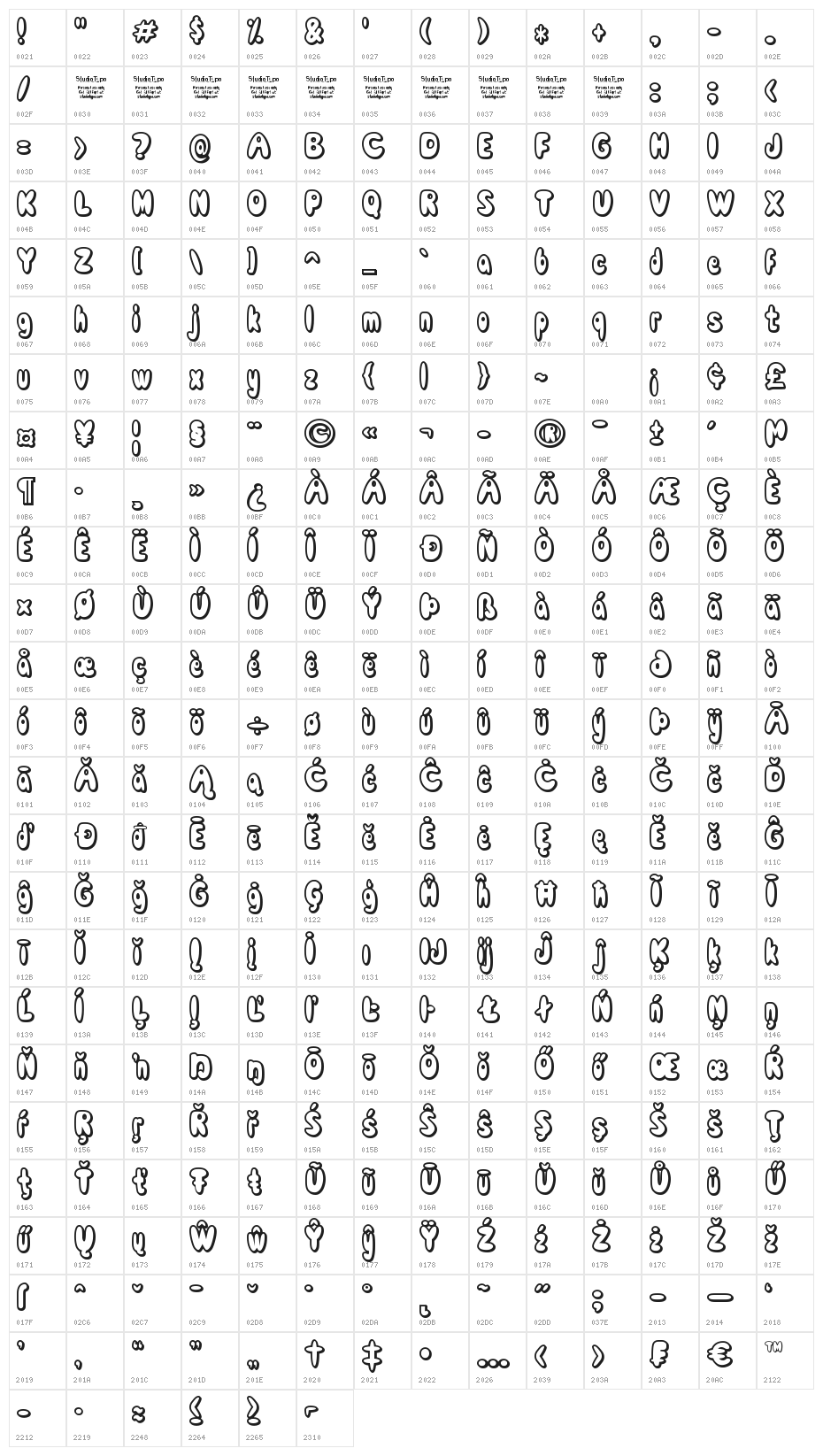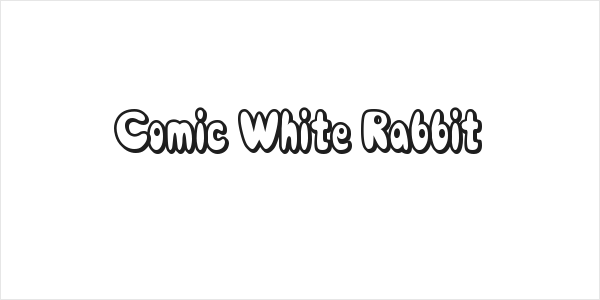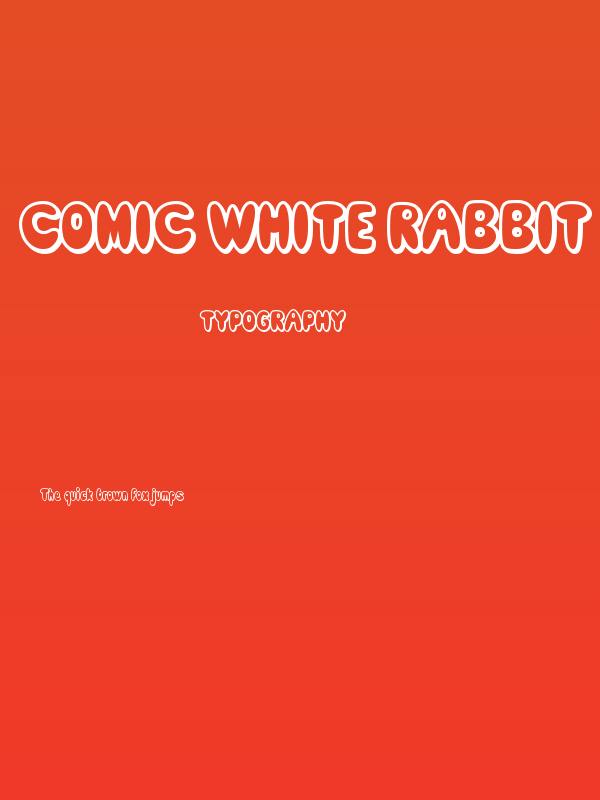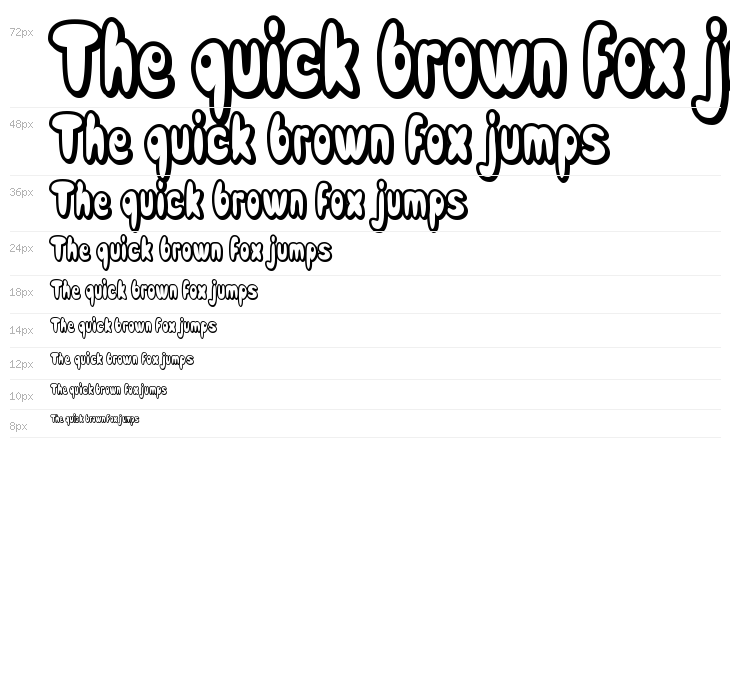
Comic White Rabbit Font
| समग्र शैली | Playful, Cartoonish |
| उपयोग का मामला | Headlines, Logos, Posters |
| सुझाए गए प्रोजेक्ट | Ideal for children's books, comic strips, playful branding, and party invitations. |